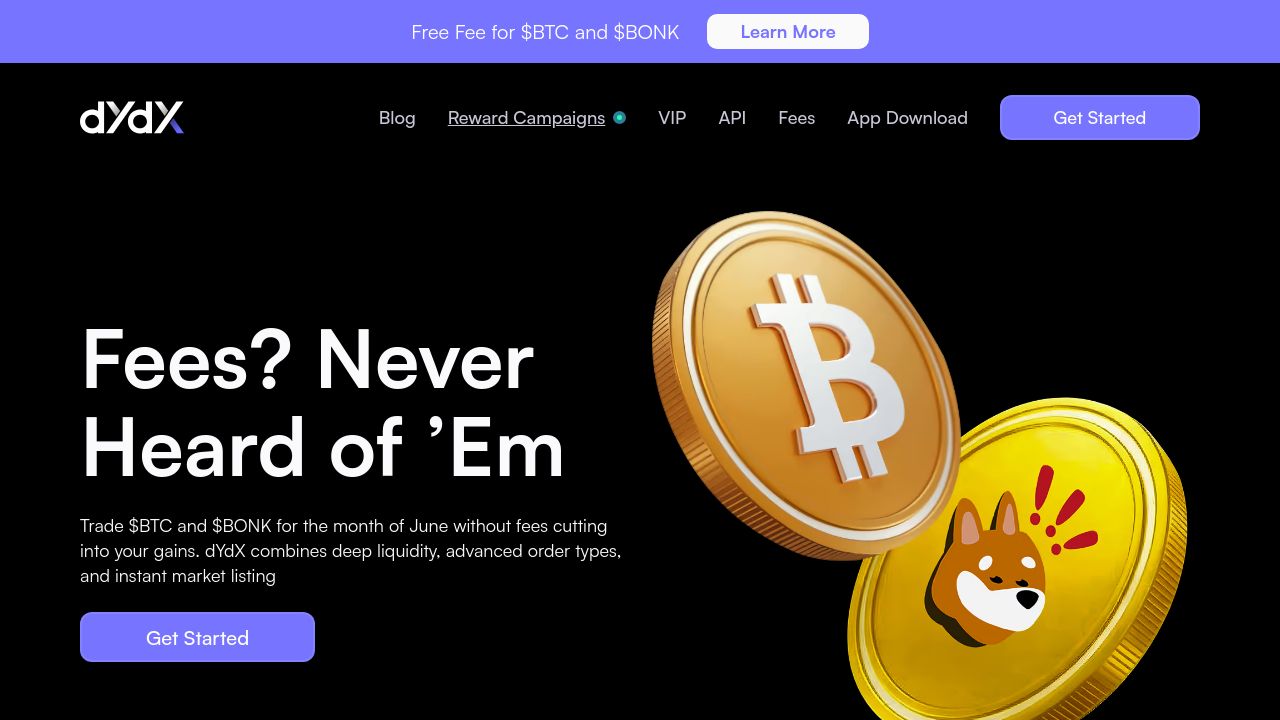
dYdX: DeFi's Pro Trading Platform
dYdX offers a decentralized trading platform designed for perpetual contracts, combining deep liquidity, advanced trading tools, and low fees. The mobile and web experience provides flexible trading options, including up to 50x buying power, with a focus on transparency and self-custody.
Dydx कौन से फ़ॉन्ट उपयोग करता है?
Dydx.exchange मुख्य फ़ॉन्ट के रूप में Satoshi, Satoshi-compressed और CourierPrime उपयोग करता है। Arial, helvetica-neue, Helvetica और Segoe UI फ़ॉलबैक के रूप में घोषित हैं। 10 फ़ॉन्ट मिले, अंतिम जांच 1 जून 2026।
dYdX एक विकेन्द्रीकृत ट्रेडिंग प्लेटफॉर्म है जो स्थायी अनुबंधों के लिए डिज़ाइन किया गया है। इस वेबसाइट पर उपयोग किए जाने वाले प्राथमिक फॉन्ट्स, जैसे Arial और Satoshi, गहराई से तरलता और उन्नत ट्रेडिंग उपकरणों की पेशकश करते हैं। ये फॉन्ट्स एक पेशेवर और स्पष्ट दृश्य पहचान को प्रकट करते हैं, जो उपयोगकर्ताओं को एक सहज ट्रेडिंग अनुभव प्रदान करता है।
Dydx.exchange कौन से फ़ॉन्ट उपयोग करता है?
Dydx.exchange मुख्य फ़ॉन्ट के रूप में Satoshi, Satoshi-compressed और CourierPrime उपयोग करता है। Arial, helvetica-neue, Helvetica और Segoe UI फ़ॉलबैक के रूप में घोषित हैं। 10 फ़ॉन्ट मिले, अंतिम जांच 1 जून 2026।
dydx.exchange पर कौन से फॉन्ट्स का उपयोग किया जाता है?
dydx.exchange पर मुख्य फॉन्ट्स में Arial, helvetica-neue, Satoshi, और CourierPrime शामिल हैं। ये फॉन्ट्स विभिन्न वजन में उपलब्ध हैं, जो वेबसाइट की पहचान को दर्शाते हैं।
Satoshi फॉन्ट अन्य फॉन्ट्स की तुलना में कैसे है?
Satoshi फॉन्ट का वजन 700 है, जो इसे एक मजबूत और ध्यान खींचने वाला विकल्प बनाता है। यह फॉन्ट पारंपरिक Arial की तुलना में अधिक आधुनिक और आकर्षक दिखता है।
dydx.exchange पर उपयोग किए गए फॉन्ट्स का स्टाइल क्या है?
dydx.exchange पर उपयोग किए गए फॉन्ट्स, जैसे Satoshi-compressed और CourierPrime, एक स्पष्ट और संरचित डिजाइन प्रदान करते हैं, जो उपयोगकर्ताओं को जानकारी को आसानी से समझने में मदद करते हैं।